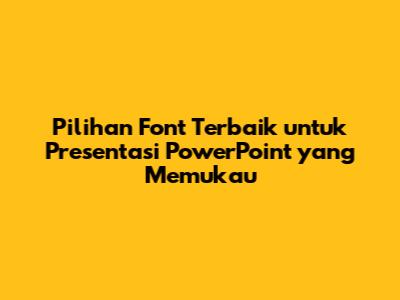
Pilihan Font Terbaik Untuk Presentasi PowerPoint Yang Memukau
Guys, siapa di sini yang sering bikin presentasi PowerPoint? Pasti udah nggak asing lagi kan sama yang namanya milih font. Nah, pemilihan font yang bagus untuk PPT itu krusial banget, lho! Soalnya, font yang tepat bisa bikin presentasi kalian lebih mudah dibaca, profesional, dan pastinya menarik perhatian audiens. Bayangin aja, kalau fontnya nggak jelas atau terlalu ramai, bukannya fokus sama materi, malah bikin pusing yang lihat. Jadi, mari kita bahas jenis font yang bagus untuk PPT, biar presentasi kalian makin kece!
Kenapa Pemilihan Font Itu Penting Banget?
Guys, pernah nggak sih kalian merasa presentasi kalian kurang nendang meskipun materinya bagus? Salah satu penyebabnya bisa jadi karena pemilihan font yang kurang tepat. Font itu ibaratnya pakaian yang kita pakai. Kalau pakaiannya keren, otomatis kita juga jadi lebih percaya diri, kan? Begitu juga dengan presentasi. Font yang bagus akan memberikan kesan yang baik, profesional, dan membuat audiens lebih tertarik untuk menyimak.
Meningkatkan Keterbacaan
Pertama, font yang tepat akan meningkatkan keterbacaan. Ini adalah poin paling penting. Jangan sampai audiens kalian kesulitan membaca tulisan di slide karena fontnya terlalu kecil, tipis, atau malah terlalu berlebihan hiasannya. Pilihlah font yang jelas dan mudah dibaca, bahkan dari jarak jauh sekalipun. Ingat, tujuan utama presentasi adalah menyampaikan informasi. Kalau informasinya nggak bisa dibaca dengan baik, ya percuma!
Menciptakan Kesan Profesional
Kedua, font bisa menciptakan kesan profesional. Ada beberapa jenis font yang lebih cocok untuk presentasi bisnis, sementara yang lain lebih cocok untuk presentasi yang lebih santai. Dengan memilih font yang tepat, kalian bisa menyesuaikan gaya presentasi dengan tujuan dan audiens kalian. Misalnya, untuk presentasi perusahaan, kalian bisa memilih font sans-serif yang bersih dan modern. Sementara untuk presentasi yang lebih kreatif, kalian bisa mencoba font serif yang elegan atau font display yang unik.
Membangun Citra Merek
Ketiga, font bisa membantu membangun citra merek. Kalau kalian sering membuat presentasi untuk perusahaan, ada baiknya kalian menggunakan font yang sesuai dengan identitas merek perusahaan. Ini akan membantu menciptakan konsistensi visual dan membuat merek kalian lebih mudah diingat oleh audiens. Perhatikan juga warna dan gaya font yang digunakan, agar sesuai dengan logo dan elemen visual lainnya.
Mempercantik Tampilan
Keempat, font yang bagus akan mempercantik tampilan presentasi. Selain aspek fungsional, font juga memiliki aspek estetika. Pilihlah font yang enak dipandang dan sesuai dengan tema presentasi kalian. Kalian bisa menggabungkan beberapa jenis font yang berbeda untuk menciptakan tampilan yang lebih menarik dan dinamis. Tapi ingat, jangan sampai berlebihan. Terlalu banyak jenis font justru bisa membuat presentasi terlihat berantakan.
Jadi, bisa disimpulkan, pemilihan jenis font yang bagus untuk PPT itu bukan hanya soal estetika, tapi juga soal fungsionalitas dan citra. Dengan memilih font yang tepat, kalian bisa membuat presentasi yang lebih efektif, profesional, dan berkesan.
Jenis-Jenis Font yang Cocok untuk PPT
Oke, sekarang kita masuk ke pembahasan utama: jenis font yang bagus untuk PPT. Ada banyak sekali jenis font di luar sana, tapi nggak semuanya cocok untuk presentasi. Berikut ini beberapa jenis font yang paling direkomendasikan:
Font Sans-Serif: Pilihan Aman dan Modern
Font sans-serif adalah pilihan yang paling aman dan populer untuk presentasi. Ciri khasnya adalah tidak memiliki "kaki" atau "serif" di ujung huruf. Font jenis ini sangat mudah dibaca, bahkan dari jarak jauh. Beberapa contoh font sans-serif yang bagus untuk PPT:
• Arial: Font klasik yang sangat populer dan tersedia di hampir semua perangkat. Arial cocok untuk berbagai jenis presentasi, mulai dari presentasi bisnis hingga presentasi pendidikan.
• Helvetica: Font yang elegan dan mudah dibaca. Helvetica sering digunakan dalam desain grafis dan presentasi profesional.
• Calibri: Font default di Microsoft PowerPoint. Calibri memiliki tampilan yang modern dan bersih. Cocok untuk presentasi yang ingin terlihat minimalis.
• Roboto: Font yang dirancang oleh Google. Roboto memiliki tampilan yang modern dan ramah. Sangat cocok untuk presentasi yang ingin terlihat kekinian.
• Open Sans: Font yang mudah dibaca dan cocok untuk berbagai ukuran. Open Sans sering digunakan dalam desain web dan presentasi.
Guys, font sans-serif adalah pilihan yang tepat kalau kalian nggak mau ribet mikir. Tinggal pilih salah satu dari beberapa contoh di atas, dan presentasi kalian dijamin akan terlihat rapi dan profesional.
Font Serif: Tampilan Elegan dan Klasik
Font serif memiliki "kaki" atau "serif" di ujung huruf. Font jenis ini memberikan kesan yang lebih elegan dan klasik. Font serif cocok untuk presentasi yang ingin memberikan kesan formal dan berkelas. Beberapa contoh font serif yang bagus untuk PPT:
• Times New Roman: Font klasik yang sering digunakan dalam penulisan dokumen. Times New Roman memberikan kesan formal dan tradisional.
• Georgia: Font yang mudah dibaca dan memiliki tampilan yang elegan. Georgia cocok untuk presentasi yang ingin terlihat lebih mewah.
• Garamond: Font yang memberikan kesan yang lebih halus dan elegan dibandingkan dengan Times New Roman.
Perlu diingat, font serif mungkin kurang cocok untuk presentasi yang menampilkan banyak teks. Sebaiknya gunakan font serif untuk judul atau poin-poin penting saja. Kalau kalian ingin menggunakan font serif, pastikan ukurannya cukup besar agar tetap mudah dibaca.
Font Display: Sentuhan Kreatif dan Unik
Font display adalah font yang memiliki tampilan yang unik dan menarik perhatian. Font jenis ini cocok untuk presentasi yang ingin memberikan kesan kreatif dan berbeda. Beberapa contoh font display yang bagus untuk PPT:
• Impact: Font yang tebal dan mencolok. Impact cocok untuk judul atau poin-poin penting yang ingin ditonjolkan.
• Bebas Neue: Font yang modern dan mudah dibaca. Bebas Neue cocok untuk presentasi yang ingin terlihat lebih santai.
• Montserrat: Font yang serbaguna dan cocok untuk berbagai jenis presentasi. Montserrat memiliki tampilan yang bersih dan modern.
Guys, font display bisa menjadi pilihan yang tepat kalau kalian ingin membuat presentasi yang lebih berkarakter. Tapi, gunakan font display dengan bijak. Jangan terlalu banyak menggunakan font display, karena bisa membuat presentasi terlihat berantakan.
Tips Tambahan dalam Memilih Font
• Ukuran Font: Pastikan ukuran font cukup besar agar mudah dibaca dari jarak jauh. Ukuran font minimal untuk teks isi biasanya adalah 24 poin, sedangkan untuk judul bisa lebih besar.
• Kombinasi Font: Jangan menggunakan terlalu banyak jenis font yang berbeda. Cukup gunakan dua atau tiga jenis font saja untuk menjaga konsistensi tampilan. Kalian bisa menggunakan satu font untuk judul dan satu font untuk isi.
• Warna Font: Pilih warna font yang kontras dengan latar belakang slide. Ini akan membuat teks lebih mudah dibaca. Hindari menggunakan warna font yang terlalu mencolok atau sulit dibaca.
• Jarak Spasi: Perhatikan jarak spasi antara huruf dan kata. Jarak spasi yang terlalu rapat atau terlalu lebar bisa membuat teks sulit dibaca.
• Konsistensi: Gunakan font yang sama di seluruh presentasi. Ini akan menciptakan tampilan yang lebih profesional dan konsisten.
Cara Menggunakan Font di PowerPoint
Guys, setelah kalian memilih jenis font yang bagus untuk PPT, saatnya untuk mengaplikasikannya di PowerPoint. Caranya gampang banget:
1. Buka PowerPoint dan buat presentasi baru atau buka presentasi yang sudah ada.
2. Pilih Teks: Klik pada kotak teks atau teks yang ingin kalian ubah fontnya.
3. Pilih Font: Di tab "Beranda" atau "Home", cari bagian "Font". Di sana, kalian bisa melihat daftar font yang tersedia.
4. Pilih Ukuran Font: Di bagian "Font", kalian juga bisa mengatur ukuran font.
5. Atur Gaya Font: Kalian bisa mem-bold, memiringkan, atau menggarisbawahi teks di bagian "Font".
6. Ulangi: Ulangi langkah-langkah di atas untuk semua teks di presentasi kalian.
Tips: Untuk menghemat waktu, kalian bisa mengubah font default di PowerPoint. Caranya, buka tab "Tampilan" atau "View", lalu pilih "Master Slide". Di sana, kalian bisa mengubah font untuk judul dan isi di semua slide.
Kesimpulan: Temukan Font yang Sempurna untuk Presentasi Kalian
Guys, memilih jenis font yang bagus untuk PPT memang membutuhkan sedikit pertimbangan. Tapi, dengan memahami jenis-jenis font dan tips yang sudah dibahas di atas, kalian bisa membuat presentasi yang lebih menarik, profesional, dan mudah dipahami. Ingat, font adalah salah satu elemen penting dalam desain presentasi. Jadi, luangkan waktu untuk memilih font yang tepat, ya! Jangan ragu untuk bereksperimen dan mencoba berbagai jenis font untuk menemukan font yang paling cocok dengan gaya presentasi kalian.